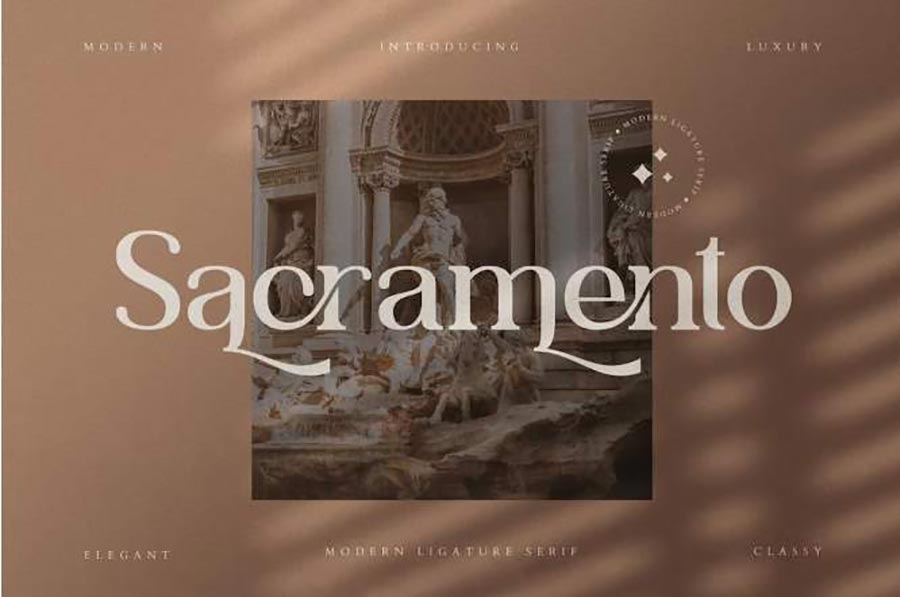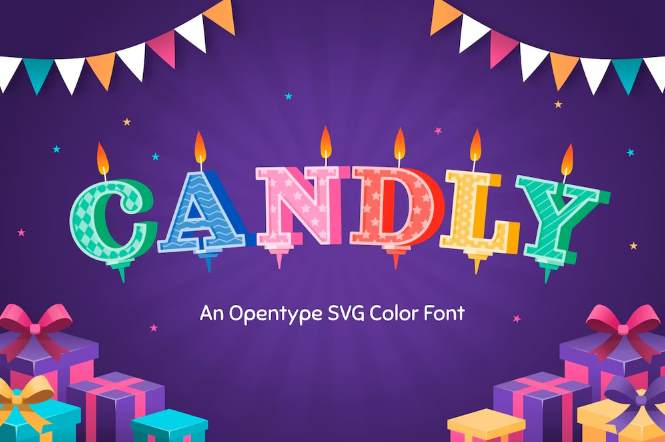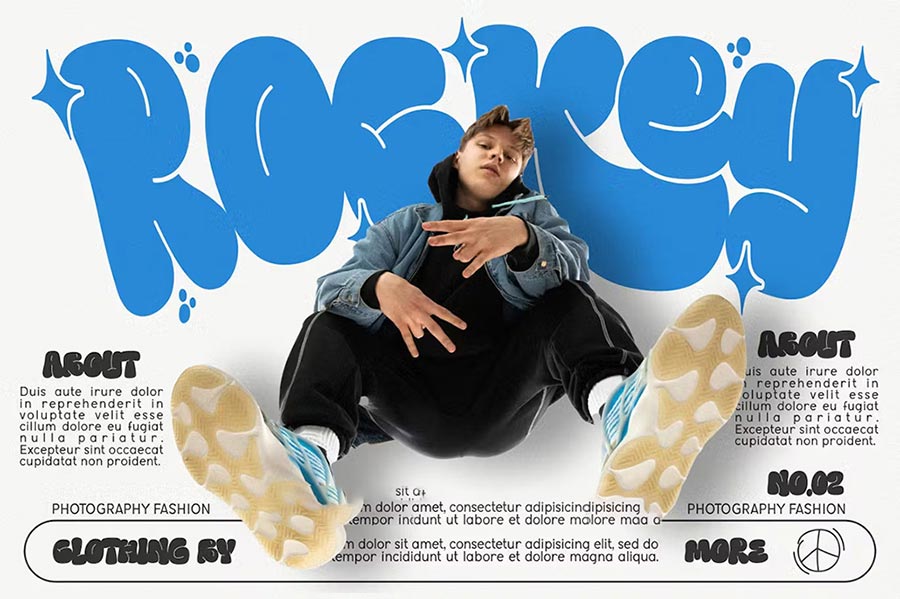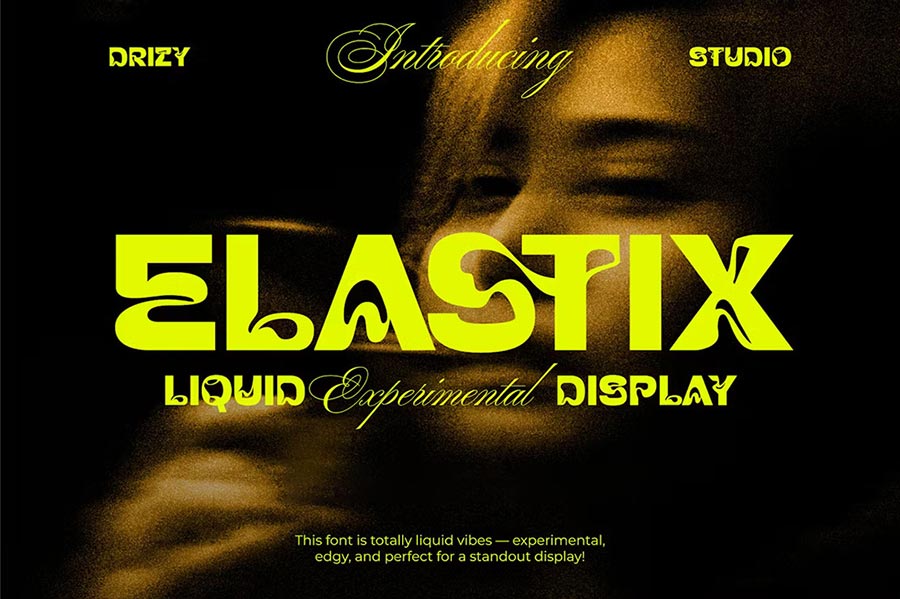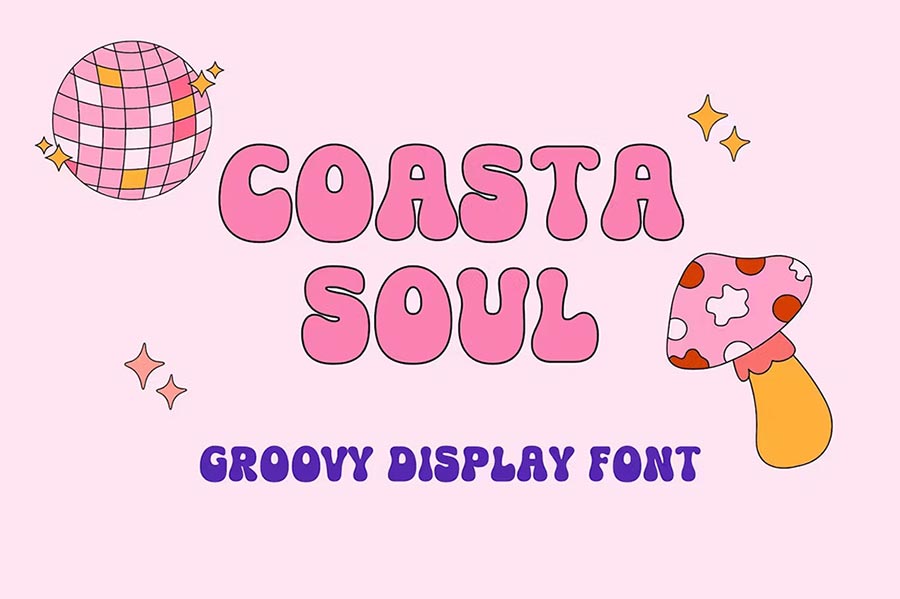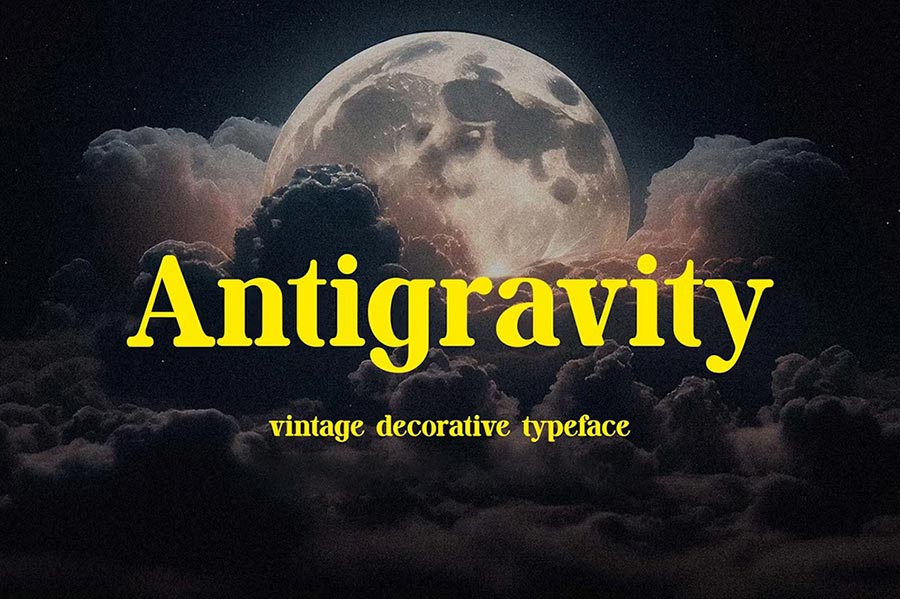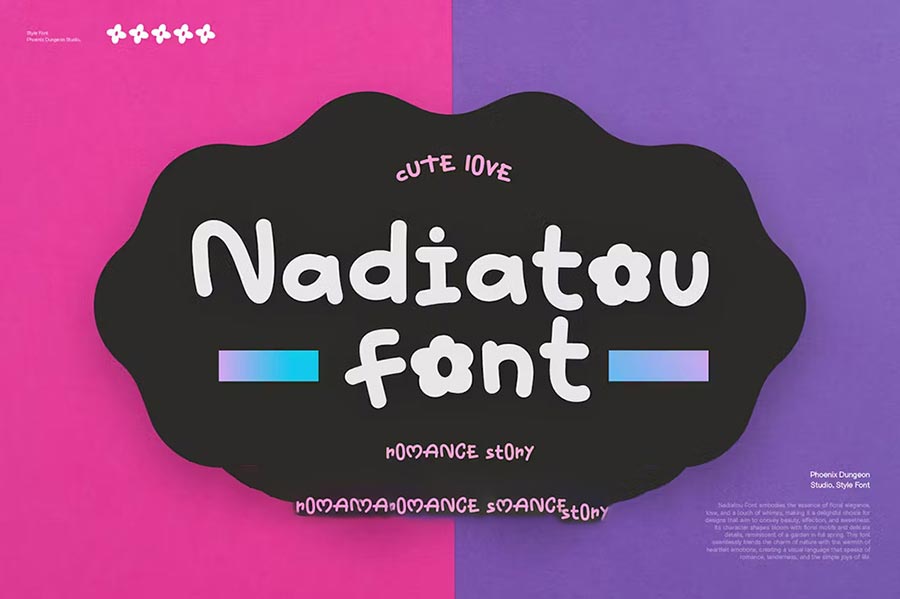
Chia Sẻ Miễn Phí Tải 6 Font Chữ Miễn Phí Tuyệt Đẹp Dành Cho Designer Mới Nhất
Trong thế giới thiết kế đồ họa, font chữ đóng vai trò vô cùng quan trọng trong việc truyền tải thông điệp và tạo ấn tượng thị giác mạnh mẽ. Hiểu được nhu cầu của các designer, Sadesign.vn đã tổng hợp và chia sẻ miễn phí 6 font chữ đẹp mắt, giúp các nhà thiết kế dễ dàng lựa chọn và sáng tạo. Hãy cùng khám phá những font chữ độc đáo này và cách chúng có thể nâng tầm dự án của bạn.
1. Giới thiệu về Sadesign.vn và Tầm Quan Trọng của Font Chữ
Font chữ không chỉ đơn thuần là công cụ truyền tải nội dung mà còn góp phần tạo nên phong cách riêng biệt cho từng dự án. Một font chữ phù hợp có thể làm nổi bật thông điệp, thu hút sự chú ý và tạo dấu ấn khó quên đối với người xem.
2. Top 6 Font Chữ Miễn Phí Tuyệt Đẹp Dành Cho Designer
Tổng hợp 6 font chữ miễn phí tuyệt đẹp dành cho các designer tân binh đến chuyên nghiệp:
1. Font Chữ Serif Cổ Điển
Font chữ Serif luôn mang lại cảm giác trang nhã và cổ điển. Với các đường nét thanh mảnh và chân chữ rõ ràng, font này thích hợp cho các dự án cần sự uy nghiêm và lịch lãm, như bìa sách, tạp chí hay các tài liệu chính thức.
2. Font Chữ Sans-Serif Hiện Đại
Đối với những thiết kế mang hơi hướng hiện đại, font Sans-Serif là lựa chọn lý tưởng. Đặc trưng bởi sự đơn giản và dễ đọc, font này phù hợp cho các dự án kỹ thuật số như website, ứng dụng di động hay các chiến dịch quảng cáo trực tuyến.
3. Font Chữ Script Tinh Tế
Font Script mang đến sự mềm mại và uyển chuyển với những đường nét uốn lượn. Đây là lựa chọn hoàn hảo cho các thiết kế cần sự lãng mạn và nghệ thuật, chẳng hạn như thiệp cưới, poster nghệ thuật hay thương hiệu thời trang.
4. Font Chữ Display Nổi Bật
Với thiết kế độc đáo và nổi bật, font Display thường được sử dụng để tạo điểm nhấn trong các tiêu đề lớn hoặc logo thương hiệu. Sự sáng tạo trong từng đường nét giúp font này thu hút ánh nhìn và dễ dàng ghi nhớ.
5. Font Chữ Monospace Cổ Điển
Monospace là loại font mà mỗi ký tự chiếm cùng một khoảng rộng, tạo nên sự đồng nhất và dễ đọc. Font này thường được sử dụng trong các tài liệu kỹ thuật hoặc giao diện lập trình viên.
6. Font Chữ Handwritten Thân Thiện
Font Handwritten mang lại cảm giác gần gũi và thân thiện với những nét chữ giống như viết tay. Đây là lựa chọn tuyệt vời cho các thiết kế mang tính cá nhân hóa cao như thiệp mời, nhật ký hay blog cá nhân.